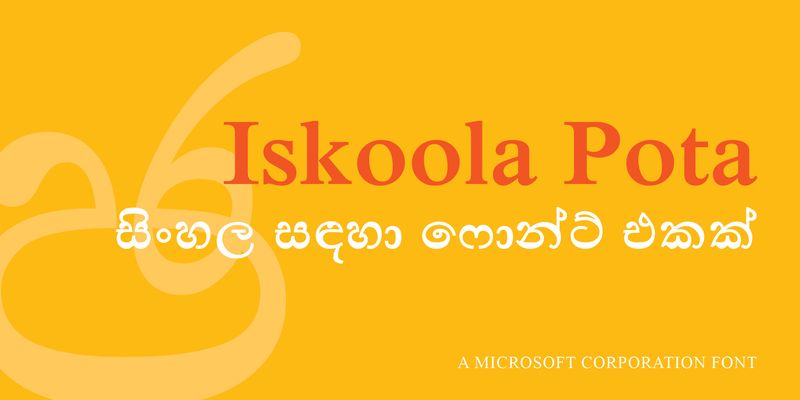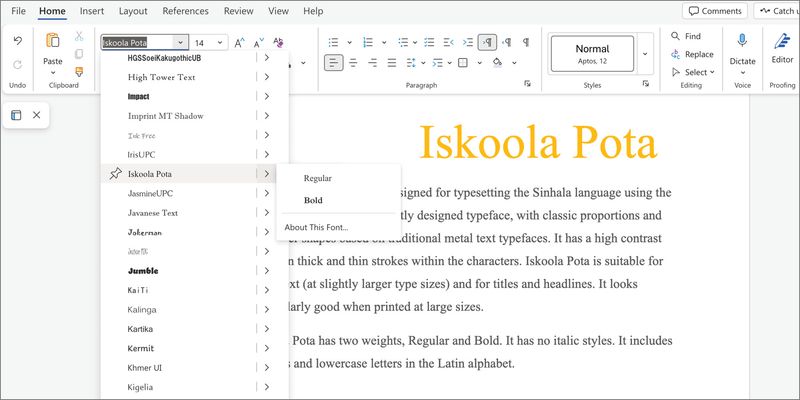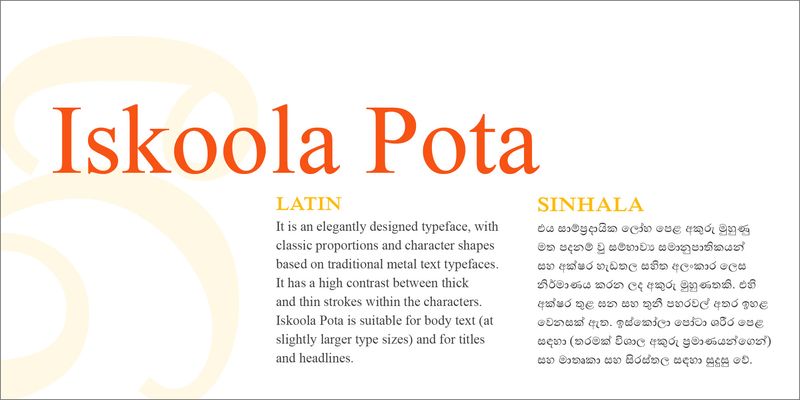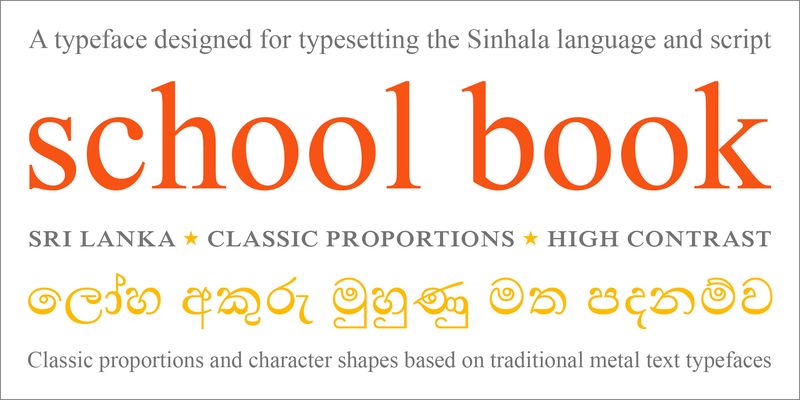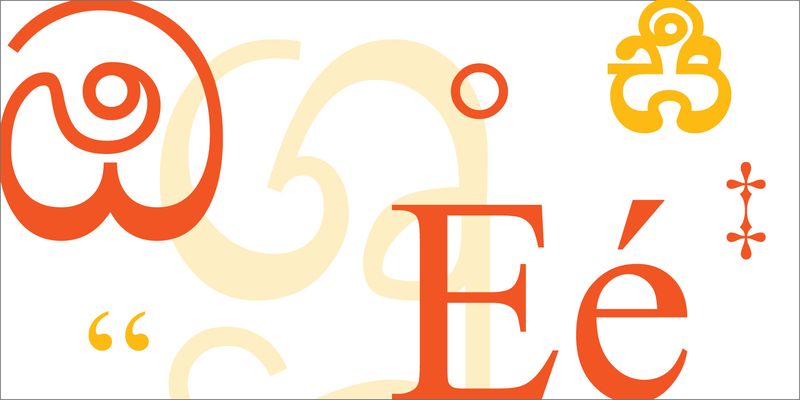
Iskoola Pota est une police de caractères conçue pour la composition typographique du cinghalais. Élégante, elle présente des proportions et des formes de caractères classiques inspirées des polices de caractères métalliques traditionnelles. Elle offre un contraste marqué entre les traits épais et fins. Elle convient au corps du texte (en corps de police légèrement plus grands) ainsi qu’aux titres et en-têtes. Son rendu est particulièrement réussi en grand format.
Iskoola Pota propose deux épaisseurs : Regular et Bold. Elle ne comporte pas d’italique. Elle inclut les majuscules et les minuscules de l’alphabet latin.